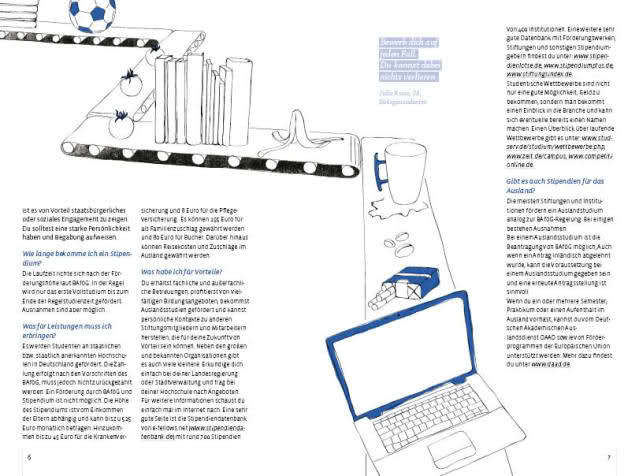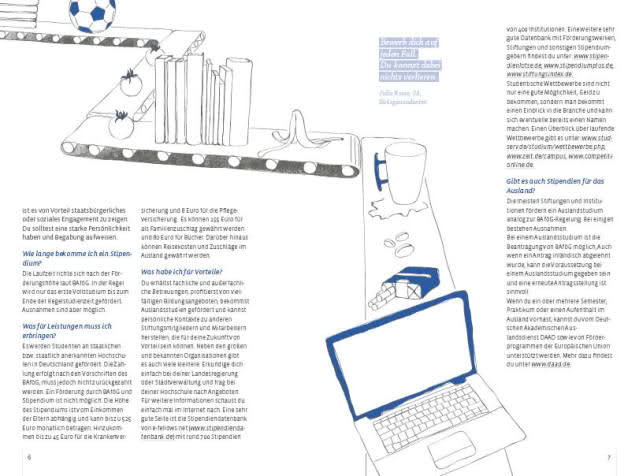
Fließtext grau oder schwarz
ich bin hin und her gerissen. anfangs hatte ich meinen fließtext in einem dunklen grau (30, 23, 26, 67) gesetzt ... und nun bin ich am überlegen, ihn doch schwarz zu machen, da in schwarz meine druckstruktur, die oft in dem buch vorkommt, besser wirkt.
was denkt ihr?
ah, vielen dank für deine schnelle antwort. momentan ist erstmal nur ein digitaldruck geplant, da ich das buch voerst nur zwei mal brauche (bachelor)...
ich weiß halt, das schwarz besser lesbar ist, aber das grau macht das gesamtlayout angenehm zart ... mmh
könnte man den text schwarz machen und die linien der illustrationen trotzdem grau lassen? oder doch alles zusammen grau?
oh ok ... das gilt dann sicherlich auch für die linien der grafik - aber auch nur im offset-druck?
würdest du aber unabhängig von dieser problematik den text grau machen?
oh ok ... das gilt dann sicherlich auch für die linien der grafik
Ja. Bei allem »feinen«.
würdest du aber unabhängig von dieser problematik den text grau machen?
Im Digitaldruck ist das Problem der Passergenauigkeit nicht ganz so problematisch – das generelle Problem des Zusammendrucks der 4 Grundfarben besteht natürlich trotzdem. Außerdem »steht« dann gegebenenfalls einfach zu viel Farbe auf dem Papier.
Teste einfach verschiedene Grauwerte auf der Digitaldruckmaschine, die du später verwenden wirst, durch. 0/0/0/40, 0/0/0/50, 0/0/0/60 und so weiter. Dann kannst du genau beurteilen, wie weit du dich vom Schwarz-Vollton entfernen kannst.
Im Digitaldruck ist das Problem der Passergenauigkeit nicht ganz so problematisch …
Im Gegenteil. In Abhängigkeit von Maschinentyp, Wetterlage und Material kann das Problem eines Farbversatzes, der dann zu unschönen Effekten und Unschärfen bei Schriften aus zusammengesetzten Farben führt, dramatischer sein als im Offsetdruck.
Jup, hab das grad mal mit verschiedenen grauwerten bis 0, 0, 0, 85 probiert und tendier im ausdruck glaube doch zu schwarz für den fließtext. lässt sich einfach besser lesen ... der kontrast ist angenehmer und das die anderen farben wirken auch stärker. vielen dank nochmal für eure tips!!!!!
Wenn Dir die Seiten momentan mit schwarzem Text und schwarzen Linien und Flächen bei den Grafiken zu "schattig" und heftig werden, dann kommen ja auch noch andere Möglichkeiten in Betracht, als Schwarz durch Grau zu ersetzen. Du könntest beispielsweise schauen ob Du von der verwendeten Schrift auch einen Light- oder Thin-Schnitt zur Verfügung hast, eventuell mit dem Zeilenabstand noch experimentieren und die schwarzen Flächen in den Grafiken durch schraffierte ersetzen. Hätte jedenfalls den Vorteil, dass alles auch bei minderwertigerem Druck vergleichsweise gestochen scharf bleibt :)
Und Du könntest über die Seitenränder nochmal nachdenken: Mir erscheinen sie ohnehin zu schmal, und etwas mehr Weißraum würde das Layout zusätzlich aufhellen :)
hab schon eine thin genommen ... ich glaube ich hatte mich einfach in den letzten wochen so an das grau gewöhnt ... und im ausdruck ist wie gesagt auch nicht mehr so derb. aber wegen den abständen werde ich nochmal schauen ... vielen dank. bis auf den rand, der ist gewollt ;)
achso aber beim schwarz nehm ich auch einfach 100 % schwarz ohne zugabe von anderen farben? hatte sowas mal woanders gelesen.
hab schon eine thin genommen ... ich glaube ich hatte mich einfach in den letzten wochen so an das grau gewöhnt ... und im ausdruck ist wie gesagt auch nicht mehr so derb.
Ja, auf einem leuchtenden Bildschirm ist's immer etwas anderes als auf Papier :D
bis auf den rand, der ist gewollt ;)
Was ja nicht heißen muss, dass das auch gut ist... :wink: :wink: :wink:
achso aber beim schwarz nehm ich auch einfach 100 % schwarz ohne zugabe von anderen farben? hatte sowas mal woanders gelesen.
Jo, bei nem Plakat mischt man eher noch CMY zu, damit es schön satt wird bei so einer großen Fläche, aber bei Schrift in Textgröße (insbesondere in Thin) und Linien lässt man das lieber bleiben, das wird unsauber :D
Sollten die Linien in der Illustration Pixelgrafiken sein, und du willst jetzt nachträglich die CMY-Kanäle rauskriegen und das Schwarz dafür satter machen, hilft dir vermutlich der Kanalmixer von Photoshop am besten weiter.
In der Photoshop-Hilfe steht genauer wo und wie.